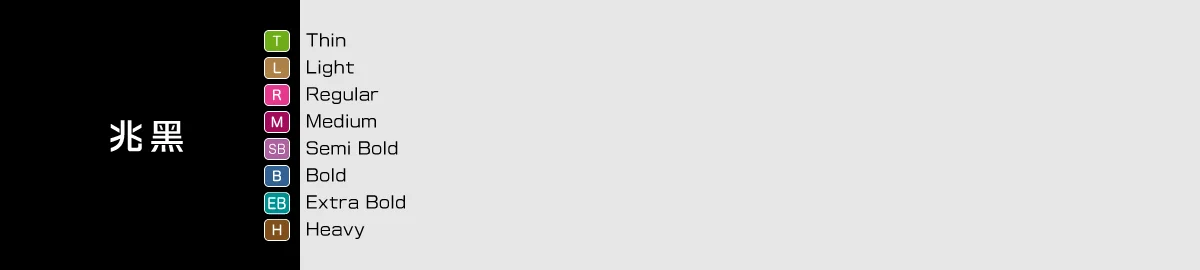
兆黑の特徴
「兆黑」は、「メガG」のデザインをベースに生まれた中国語(簡体)書体です。『アンバランスな美しさ』をコンセプトに、デフォルメの限界に挑戦したクリエイティブなゴシック体です。文字としての美しさと気品を保ちながら、強い個性を印象づける絶妙なバランス感を追求しました。可読性を損なうことなく、軽やかなリズム感とイキイキとした表情を生み出します。
方正VDL兆黑-T
方正VDL兆黑-L
方正VDL兆黑-R
方正VDL兆黑-M
方正VDL兆黑-SB
方正VDL兆黑-B
方正VDL兆黑-EB
方正VDL兆黑-H